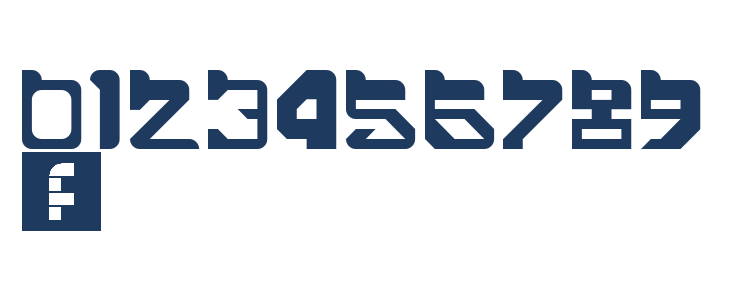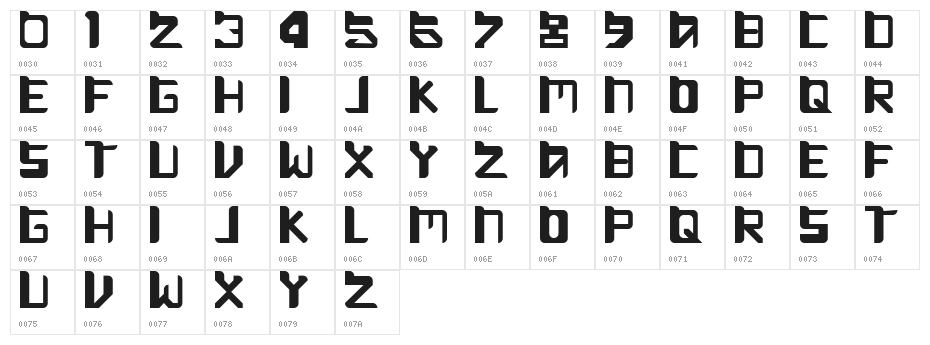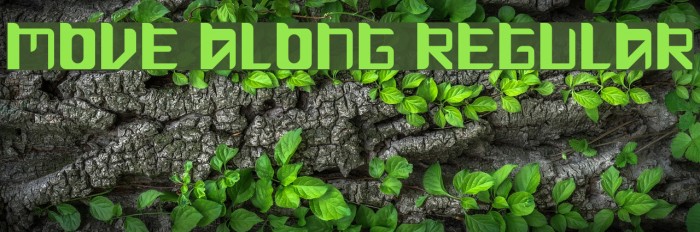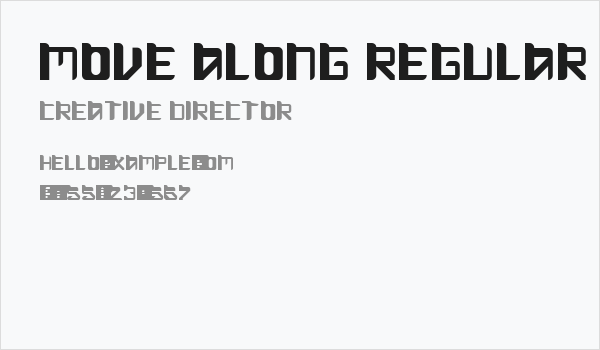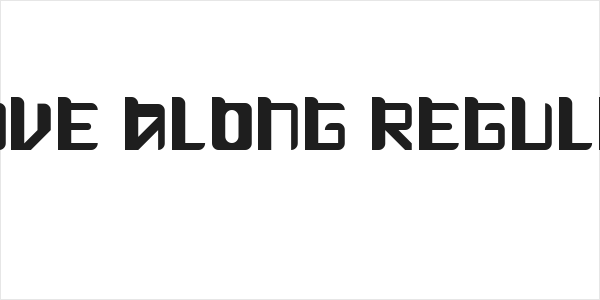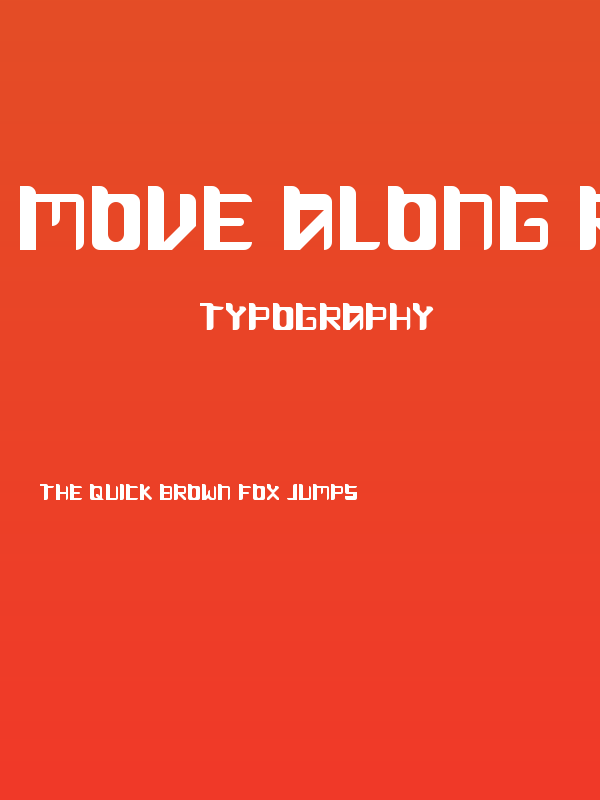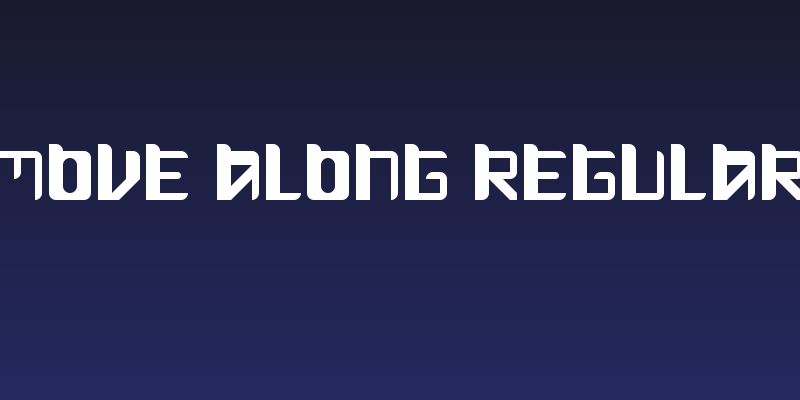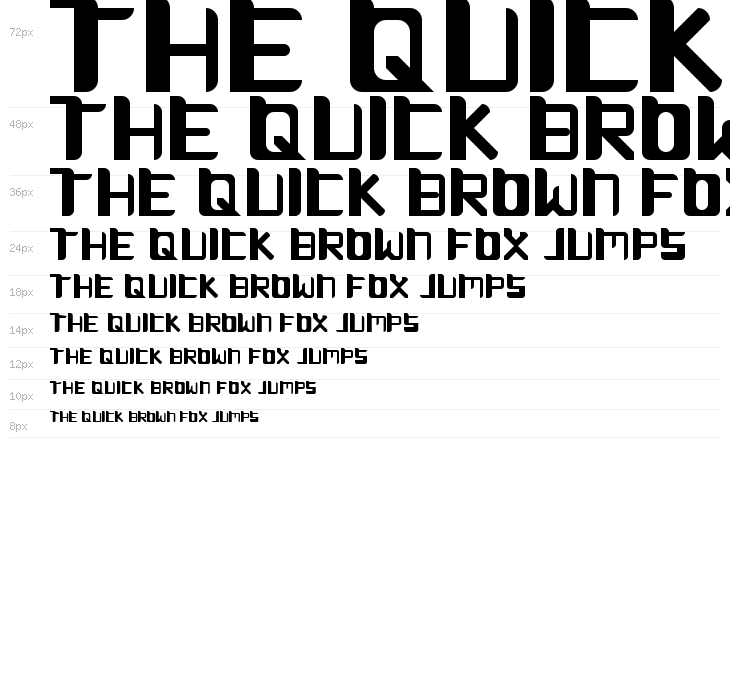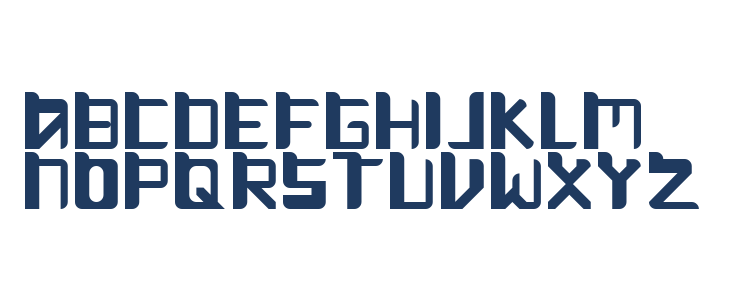
Move Along Regular Font
| Vorgeschlagene Projekte | Ideal for sci-fi themed designs, video game titles, posters, and branding that requires a modern and bold statement. |